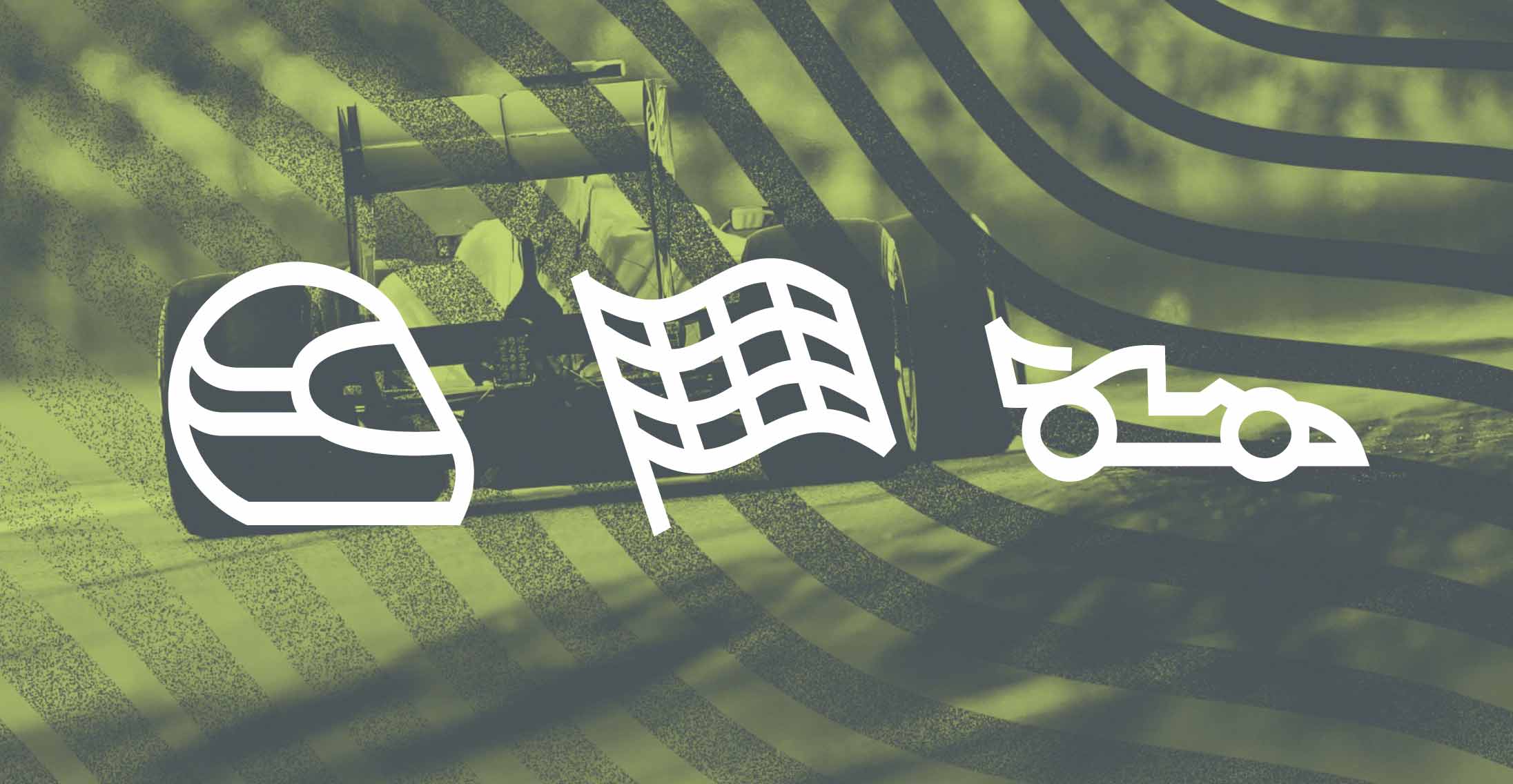
Pictogramas SporTV
Existem muitos pictogramas disponíveis, assim como existem muitas fontes prontas. E assim como algumas marcas não se contentam com soluções prontas, existem aquelas que querem pictogramas para chamar de seus.
Os canais SporTV agora contam com mais de 100 pictogramas exclusivos desenvolvidos pela Fabio Haag Type. Do futebol ao tênis, do clima às lutas, todos os temas possuem pictogramas alinhados ao universo visual dos canais.
O conceito visual é bastante expressivo por diversos motivos: a espessura dos traços horizontais é maior que a dos verticais, gerando uma sensação de verticalidade que se impõe. Este contraste grosso/fino é exatamente o oposto do que estamos acostumados nas letras latinas, resultando em pictogramas bastante expressivos.
O resultado é um conjunto com temas variados, uniforme em seu estilo proprietário. Eles são acessíveis através de uma fonte digital, em três pesos, além de uma variedade de formatos de imagens, facilitando a implementação gradual pela SporTV.
Agora, mesmo o intervalo do seu esporte favorito não é motivo para trocar de canal, estes pictogramas você só vê no canal campeão \o/